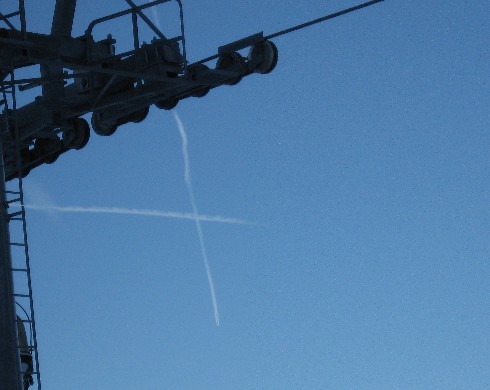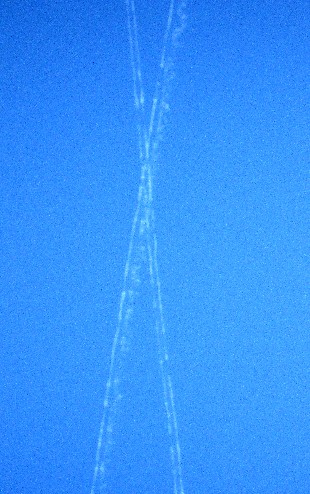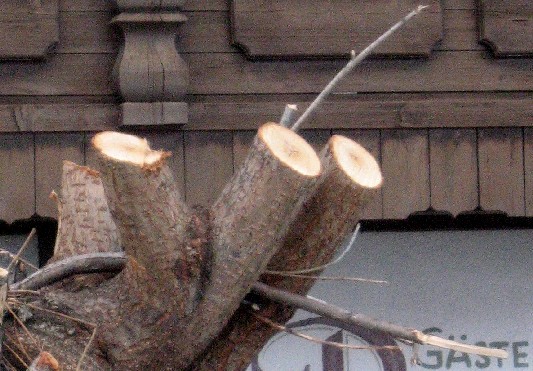
自然の中からアルファベット
アハッ体験に基づくアルファベット発見(無理やりに近い状況とも
言いいますが…)!
mojitor-sさんが洗濯バサミの中に「A」を発見してから私も
どこかにアルファベットが見つからないかいなぁ〜と結構
キョロちゃんしています。
これは、「もしかしてY」見事にすっぱと切られた枝の一部です。
うう〜ん。少し苦しいけど…一応候補です。もうちょっと「絶対Y」が見つかるまでは…。
スキー場では青空のもと太陽の産物「影のX」!
ストックもオブジェ化して、影は文字化…?いいのかな…ちょっと
やらせ気味?
そこで「ちょっと待った!」
そうよね…そうよねぇ〜。
まぁ影という手もありですけど〜!
もうちょっと探そう、探そう〜。
これは本当に偶然ですよ〜。
飛行機雲が交差して「X飛行機雲編」です。
「ああ〜雲がなくなる〜」と叫びながら、
必至に撮影…。
雄大なXでしょう?
判定は?
雪上の猫さんも「いいんじゃな〜い?」
コタツで丸くならない猫さん!北国育ちで丈夫です!
あははっ 端から端まで楽しいですねー好きです♪
「影のX」!なんかカッコイイ!
「影のX」って名前の方がカッコイイ感じですねぇ…。
「もしかしてY」は見るたびに「Y」っぽくなくなって
きたので、探しま〜す!